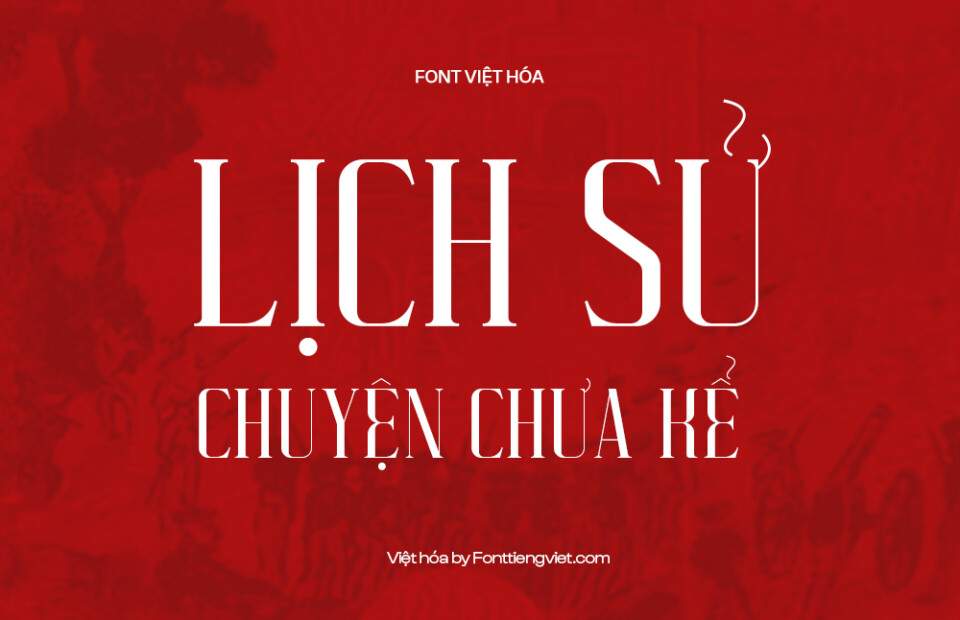
Font việt hóa 1FTV VIP Velazquez
Font việt hóa 1FTV VIP Velazquez – Bộ font cổ điển sang trọng cho thiết kế chuyên nghiệp
Giới thiệu về bộ Font việt hóa 1FTV VIP Velazquez
Trong thế giới thiết kế đồ họa hiện đại, việc tìm kiếm một bộ Font Miễn Phí có khả năng truyền tải được tinh thần nghệ thuật cổ điển xen lẫn nét tinh tế hiện đại là điều không hề dễ dàng. Font việt hóa 1FTV VIP Velazquez chính là câu trả lời hoàn hảo cho những nhà sáng tạo đang tìm kiếm sự khác biệt. Đây là một bộ phông chữ được lấy cảm hứng từ những đường nét kiến trúc và hội họa của thời kỳ Phục hưng, mang lại cảm giác vương giả và đầy quyền lực cho mọi tác phẩm. Đặc biệt, phiên bản này đã được đội ngũ 1FTV thực hiện việt hóa chỉn chu, giúp các bạn học sinh, sinh viên và nhà thiết kế tại Việt Nam có thể sử dụng dễ dàng mà không lo lỗi font khi gõ tiếng Việt. Sự tỉ mỉ trong từng nét chữ giúp bộ font này trở thành lựa chọn ưu tiên cho các dự án mang tính biểu tượng cao.
Đặc điểm nổi bật của Font việt hóa 1FTV VIP Velazquez
Phong cách thiết kế Serif độc đáo
Đặc trưng lớn nhất của Font việt hóa 1FTV VIP Velazquez nằm ở cấu trúc Serif (chữ có chân) cực kỳ thanh mảnh nhưng vẫn đảm bảo độ chắc chắn. Các đường nét được gọt giũa mềm mại, tạo nên một nhịp điệu thị giác uyển chuyển trên mặt giấy hoặc màn hình điện tử. Điều này giúp bộ chữ không chỉ dễ đọc mà còn tạo ra một không gian nghệ thuật sang trọng cho người xem. Font chữ này phản ánh sự giao thoa giữa truyền thống và tương lai, phù hợp cho cả in ấn sách báo lẫn hiển thị trên các nền tảng web hiện đại. Việc tối ưu hóa khoảng cách giữa các chữ cái (kerning) cũng được thực hiện rất kỹ lưỡng, đảm bảo tính thẩm mỹ cao nhất trong mọi hoàn cảnh sử dụng.
Khả năng ứng dụng đa dạng trong thực tế
Dù mang trong mình phong cách cổ điển, nhưng Font việt hóa 1FTV VIP Velazquez lại vô cùng linh hoạt. Bạn có thể sử dụng bộ font này để thiết kế bìa sách giáo khoa, làm tiêu đề cho các báo cáo học tập xuất sắc hoặc tạo ra những tấm thiệp mời trang trọng. Đối với các bạn yêu thích làm video hay làm nội dung trên mạng xã hội, bộ font này giúp tạo điểm nhấn mạnh mẽ cho các trích dẫn (quotes) hoặc tiêu đề phim ngắn. Sự chỉn chu trong bản việt hóa giúp các dấu câu tiếng Việt như dấu huyền, dấu sắc, dấu hỏi được đặt ở vị trí hợp lý, không làm mất đi cấu trúc tổng thể của con chữ ban đầu, mang lại sự chuyên nghiệp tuyệt đối cho người dùng.
Tại sao bạn nên sở hữu Font việt hóa 1FTV VIP Velazquez ngay hôm nay?
Kết luận về bộ font đẳng cấp